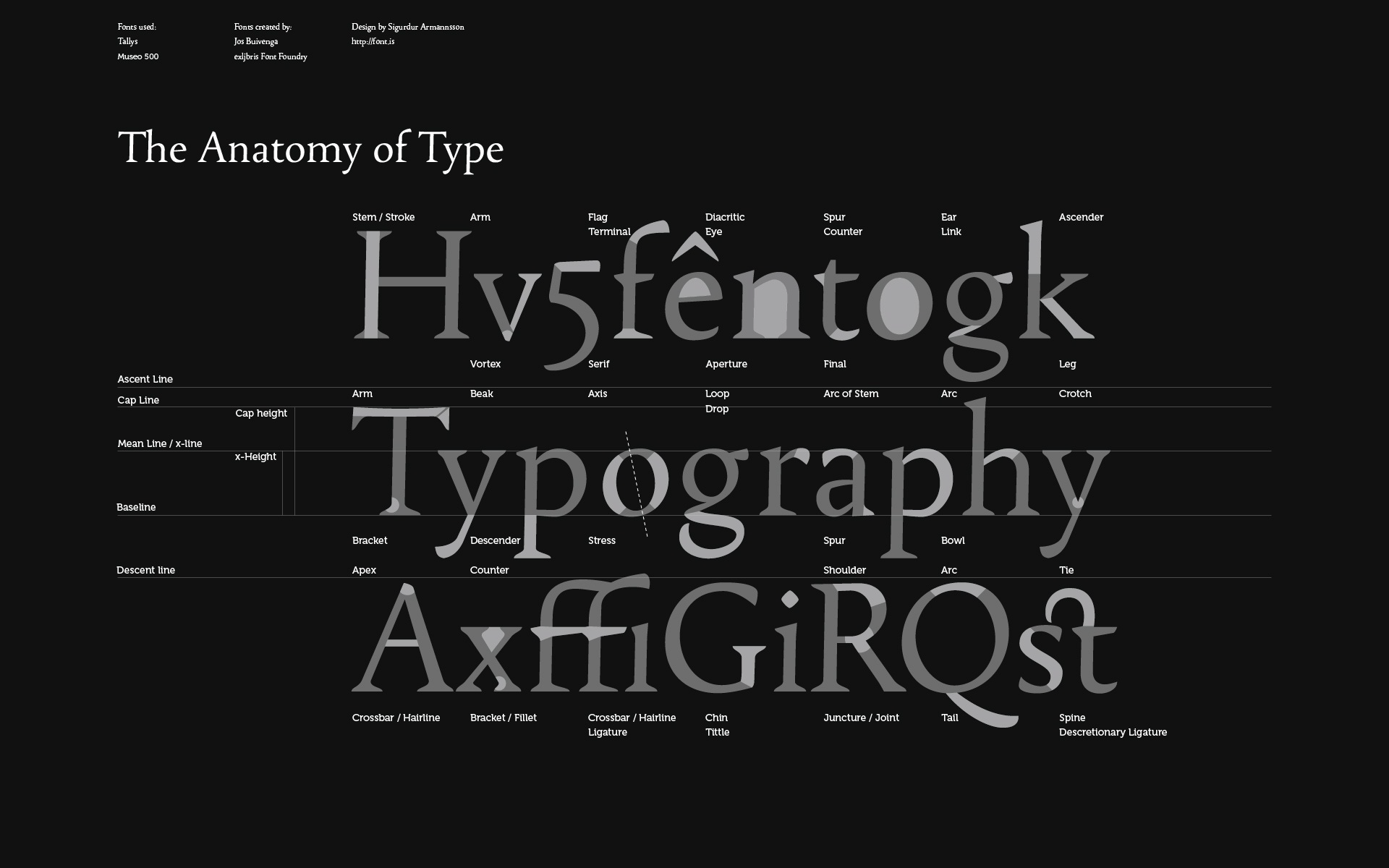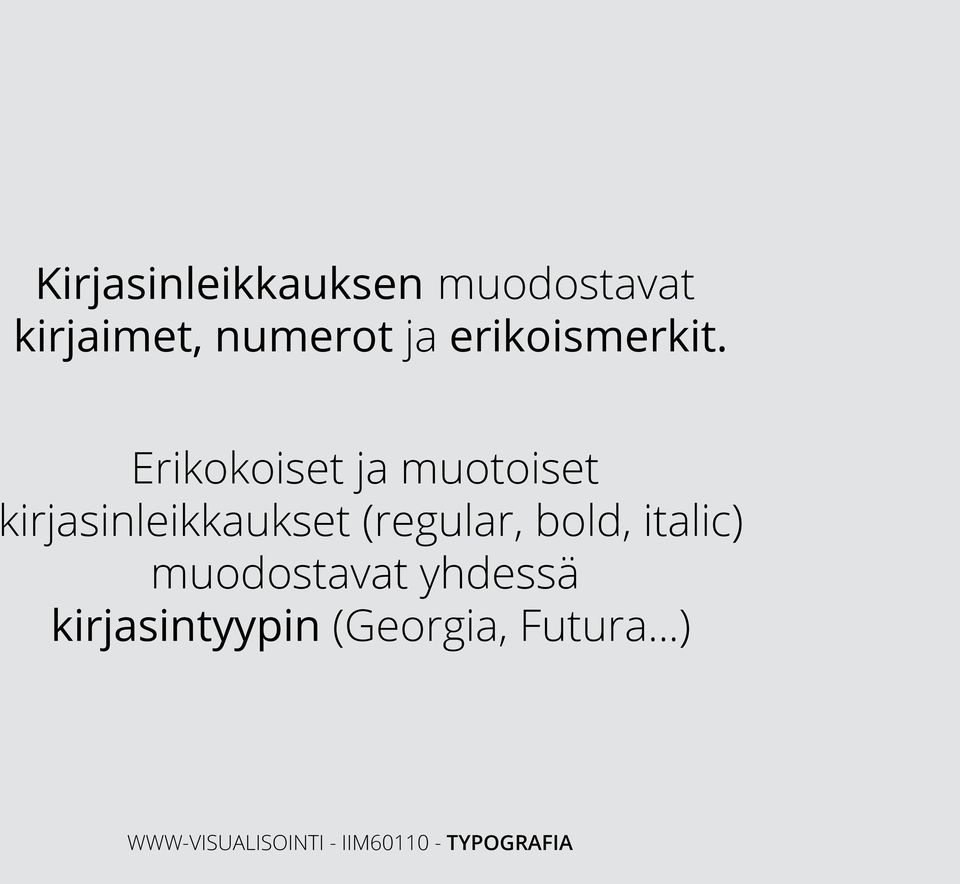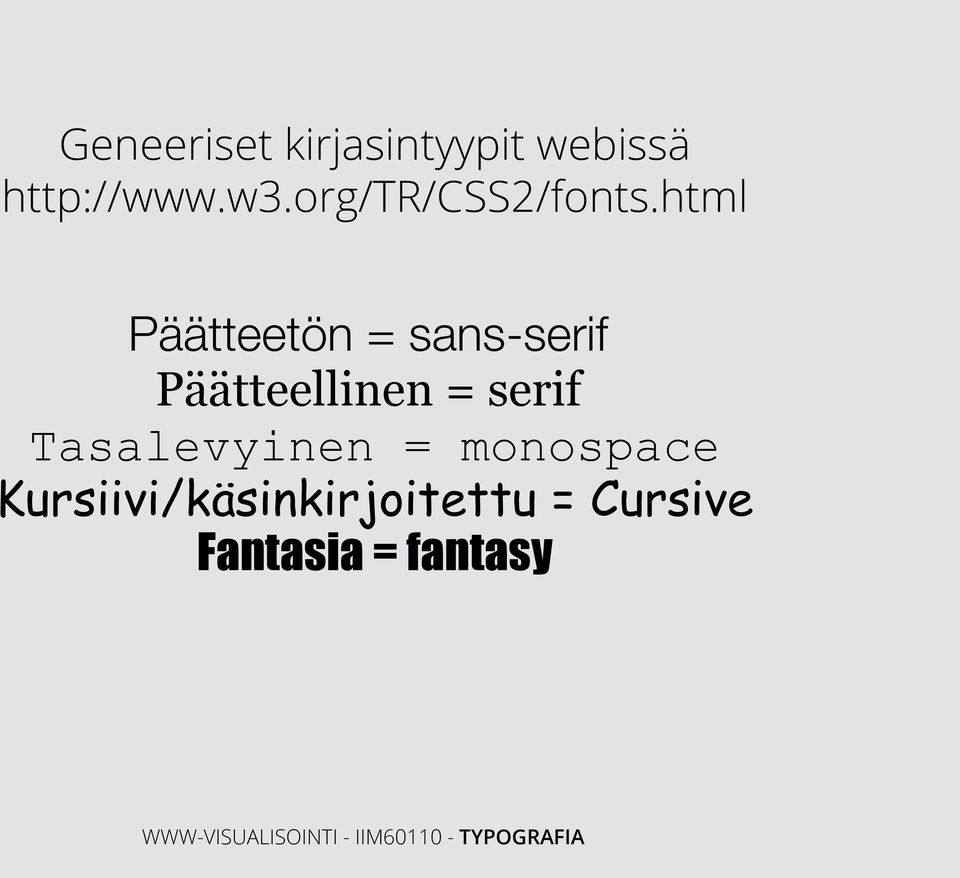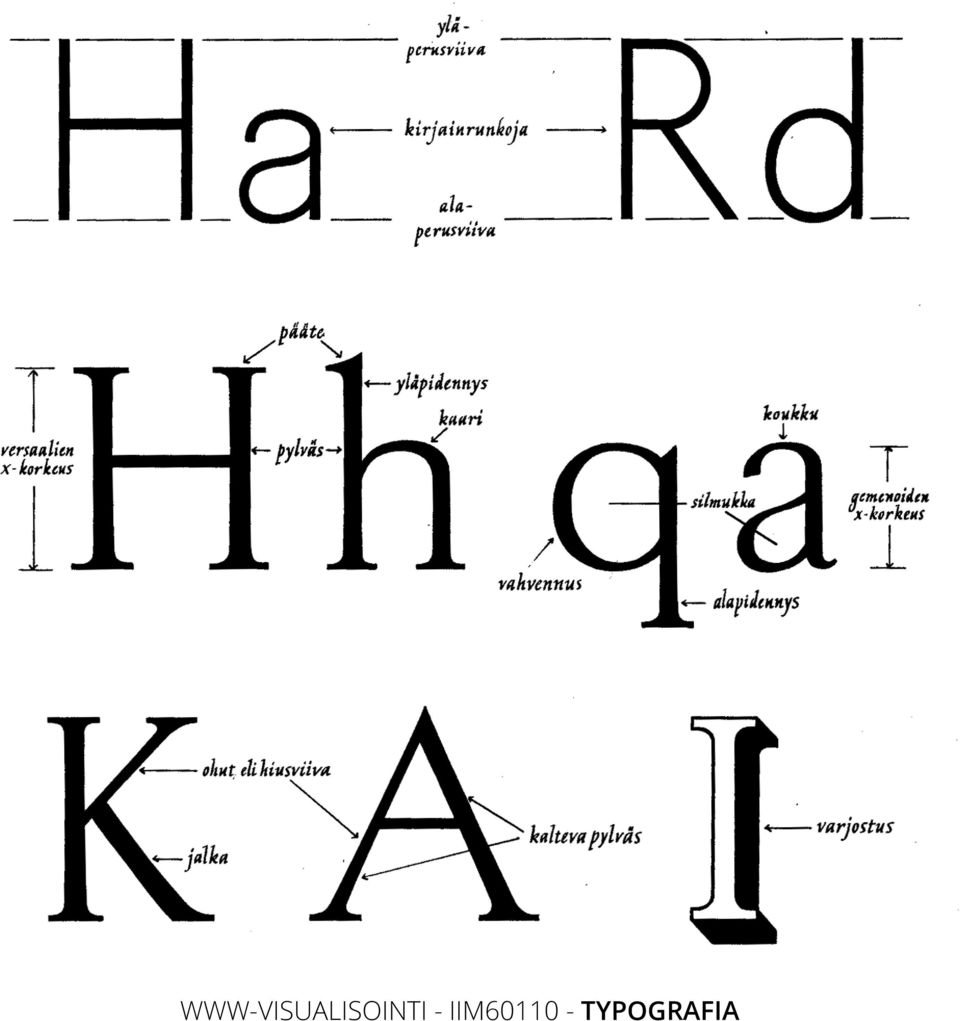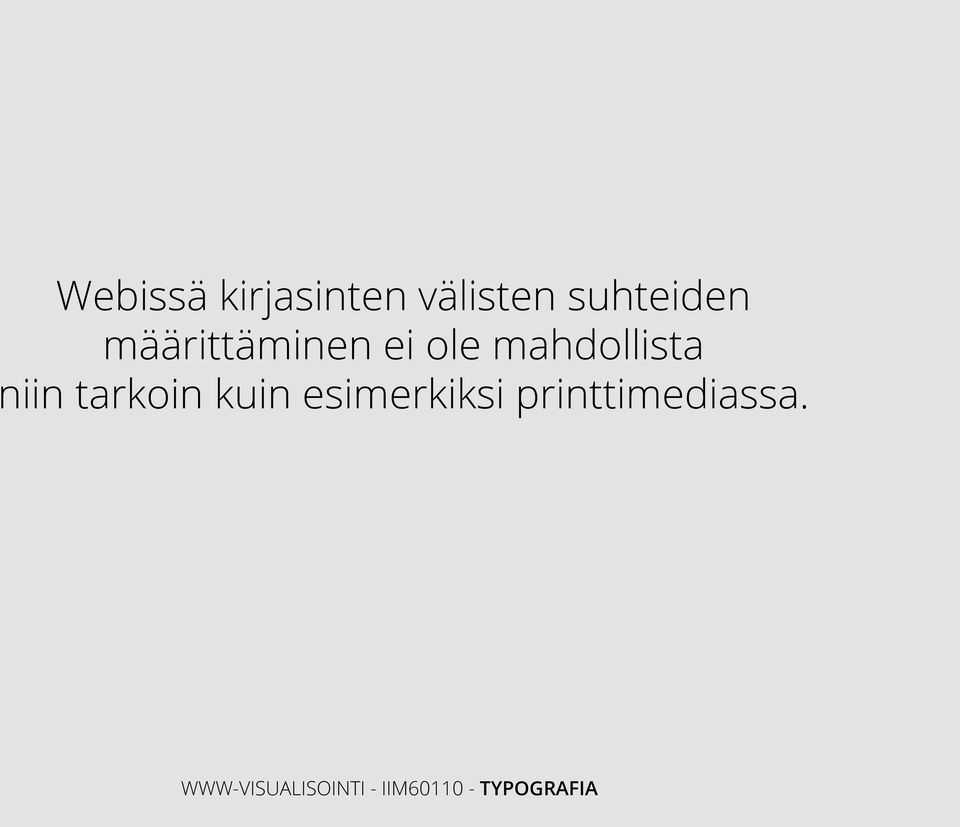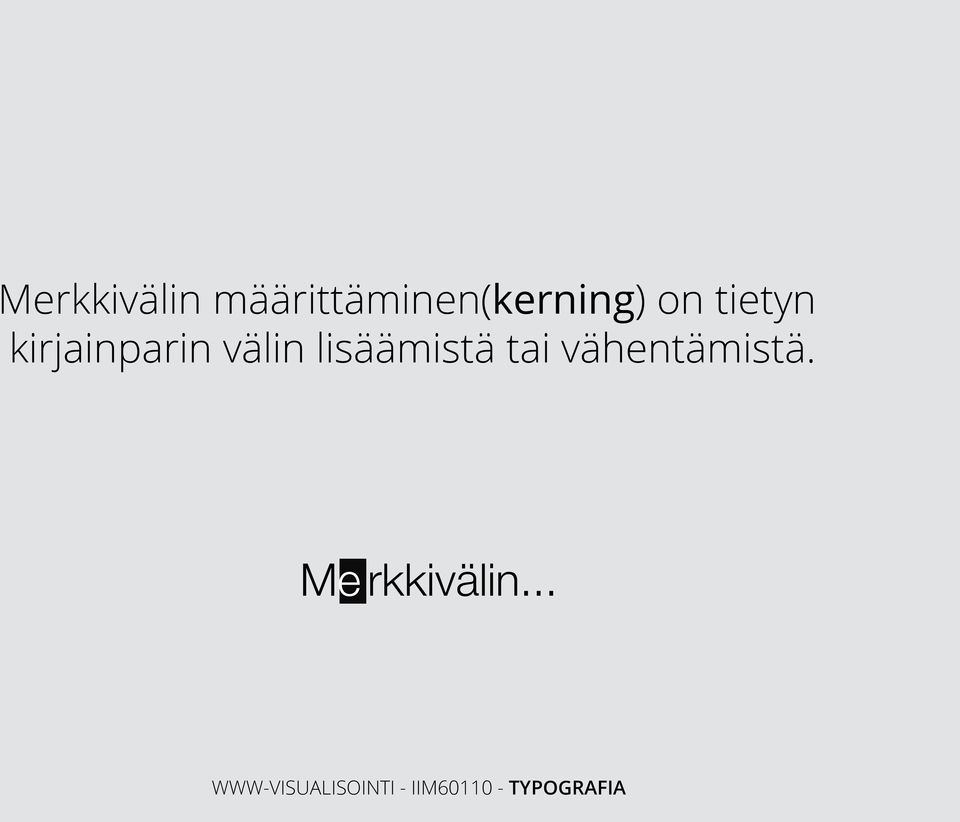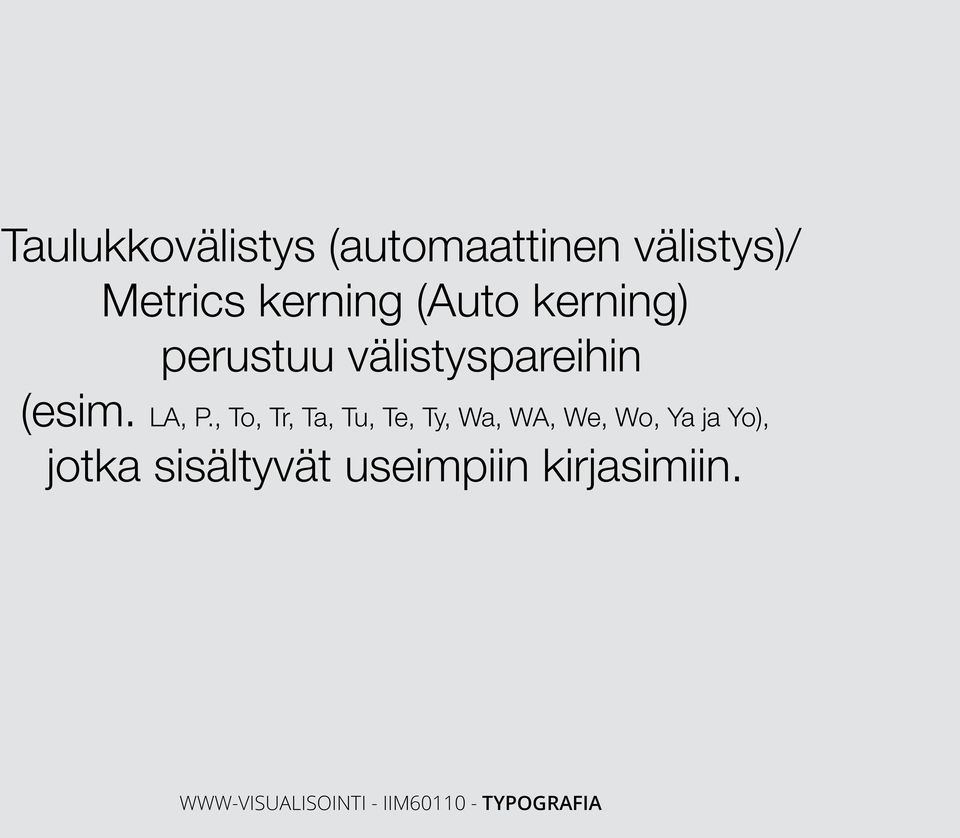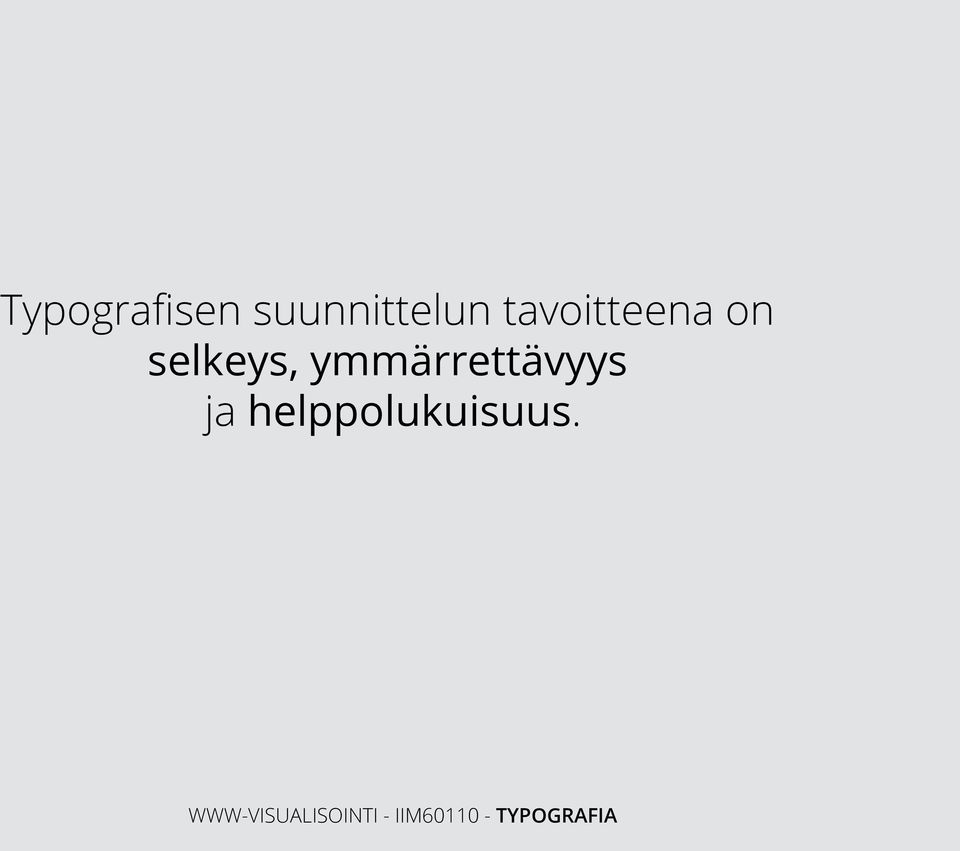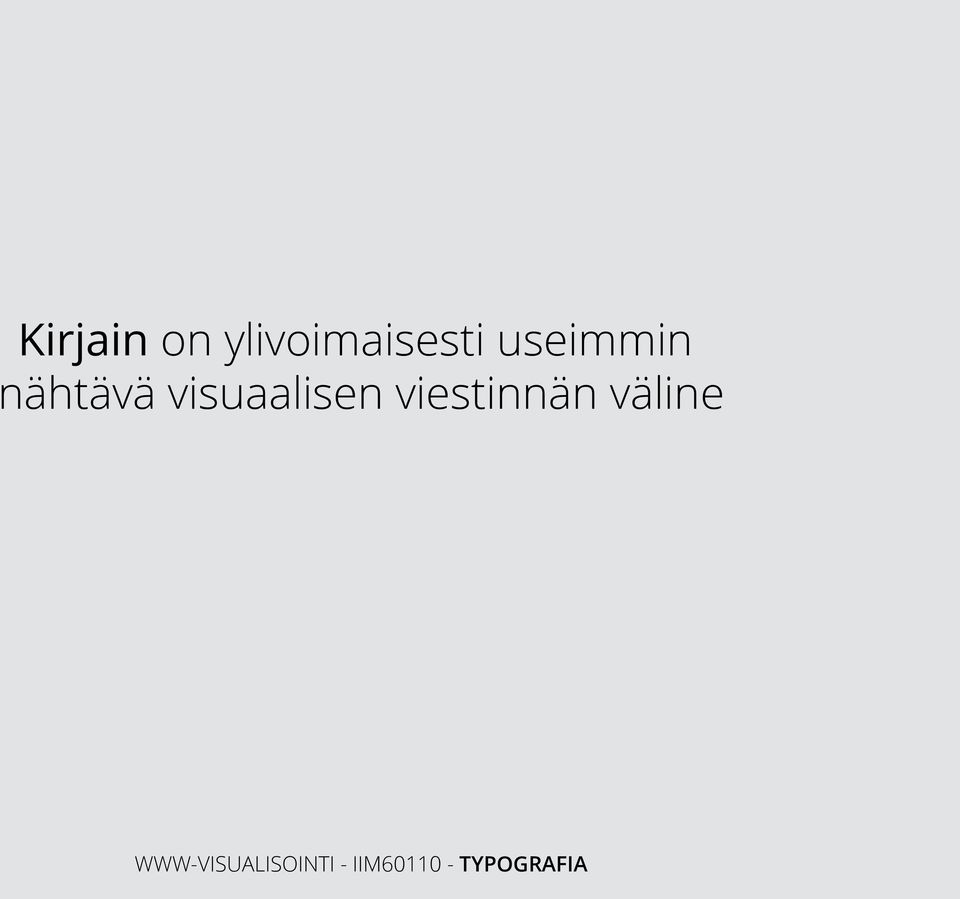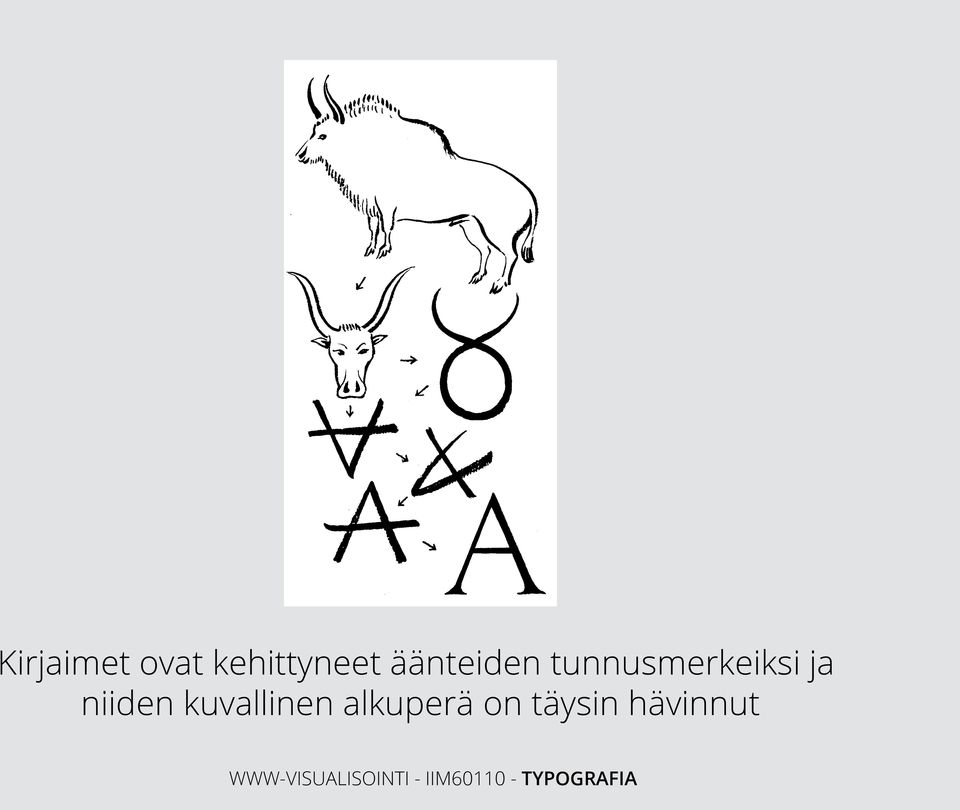
2 Kirjain on ylivoimaisesti useimmin nähtävä visuaalisen viestinnän väline
3 Kirjainmuodot ja niiden kehitys ovat aina olleet tiiviisti yhteydessä käytettyihin kirjoitusmenetelmiin. Papyrus/ruokokynä, meisselikirjoitus/kivi, kirjakepatriisit(kirjapainotaito)/paperi.
4 Kirjaimet ovat kehittyneet äänteiden tunnusmerkeiksi ja niiden kuvallinen alkuperä on täysin hävinnut
5 Kreikkalaiset täsmensivät kirjoitusmerkkien graafista muotoa ja muodostivat yhtenäisen aakkoston. Roomalaiset ottivat esikuvaksi kreikkalaisen aakkoston ja kehittivät sen pohjalta oman latinalaisen aakkostonsa.
6 Kaikkien suuraakkosten perusmuodot löytyvät geometrisista peruskuvioista.
7 Roomalaiset meisselikirjaimet 2. vuosisadan alusta.
8 Kehitys suuraakkosista pienaakkosiksi.
9 Versaali = suuraakkonen Gemena = pienaakkonen
10 Kirjasinleikkauksen muodostavat kirjaimet, numerot ja erikoismerkit. Erikokoiset ja muotoiset kirjasinleikkaukset (regular, bold, italic) muodostavat yhdessä kirjasintyypin (Georgia, Futura...)
11 Yksinkertaisin kirjasintyyppien lajitteluperuste on päätteettömiin ja päätteellisiin Päätteetön = Groteski/sans-serif Päätteellinen = Antiikva/serif
12 Geneeriset kirjasintyypit webissä Päätteetön = sans-serif Päätteellinen = serif Tasalevyinen = monospace Kursiivi/käsinkirjoitettu = Cursive Fantasia = fantasy font: normal 12px/17px Arial, Helvetica, sans-serif;
15 Webissä kirjasinten välisten suhteiden määrittäminen ei ole mahdollista niin tarkoin kuin esimerkiksi printtimediassa.
16 Merkkivälin määrittäminen(kerning) on tietyn kirjainparin välin lisäämistä tai vähentämistä. Me rkkivälin...
17 Merkkitiheyden määrittäminen(tracking) on valitun tekstin tai koko tekstilohkon merkkien välisen etäisyyden suurentamista tai tiivistämistä. Merkkitiheyden...
18 Taulukkovälistys (automaattinen välistys)/ Metrics kerning (Auto kerning) perustuu välistyspareihin (esim. LA, P., To, Tr, Ta, Tu, Te, Ty, Wa, WA, We, Wo, Ya ja Yo), jotka sisältyvät useimpiin kirjasimiin.
19 Typografisen suunnittelun tavoitteena on selkeys, ymmärrettävyys ja helppolukuisuus.
22 Typografisilla valinnoilla luot kontrastia ja jännitettä sisältöön. kevyt - raskas ISO - pieni sans-serif - serif
23 Fonttien valitseminen www-layoutiin, Serif vai Sans-serif?
24 Suurikokoiset päätteelliset fontit ovat helppolukuisia ja näyttäviä. Niitä käytetään usein otsikoinneissa.
25 Leipätekstissä voi käyttää sekä päätteellistä että päätteetöntä fonttia.
26 Mikäli käytät päätteellistä fonttia leipätekstissä, varmista että sen koko on riittävä. Esimerkkilause pienikokoisella sans-serif -fontilla - Esimerkkilause pienikokoisella serif-fontilla
27 Fonttien yhdistäminen layoutissa 1. Vältä kahden samaan perheeseen kuuluvan fontin yhdistämistä (Futura - Myriad, Bodoni - Didot) 2. Vältä kahden vahvan fontin yhdistämistä 3. Jos mahdollista, katso että x-korkeus ja välistys ovat mahdollisimman samankaltaisia kummassakin fontissa 4. Serif + Sans-serif yhdistelmä on usein tehokas 5. Kiinnitä huomiota kirjasinten muotoihin, löytyykö niistä saman tyyppisiä muotoja.